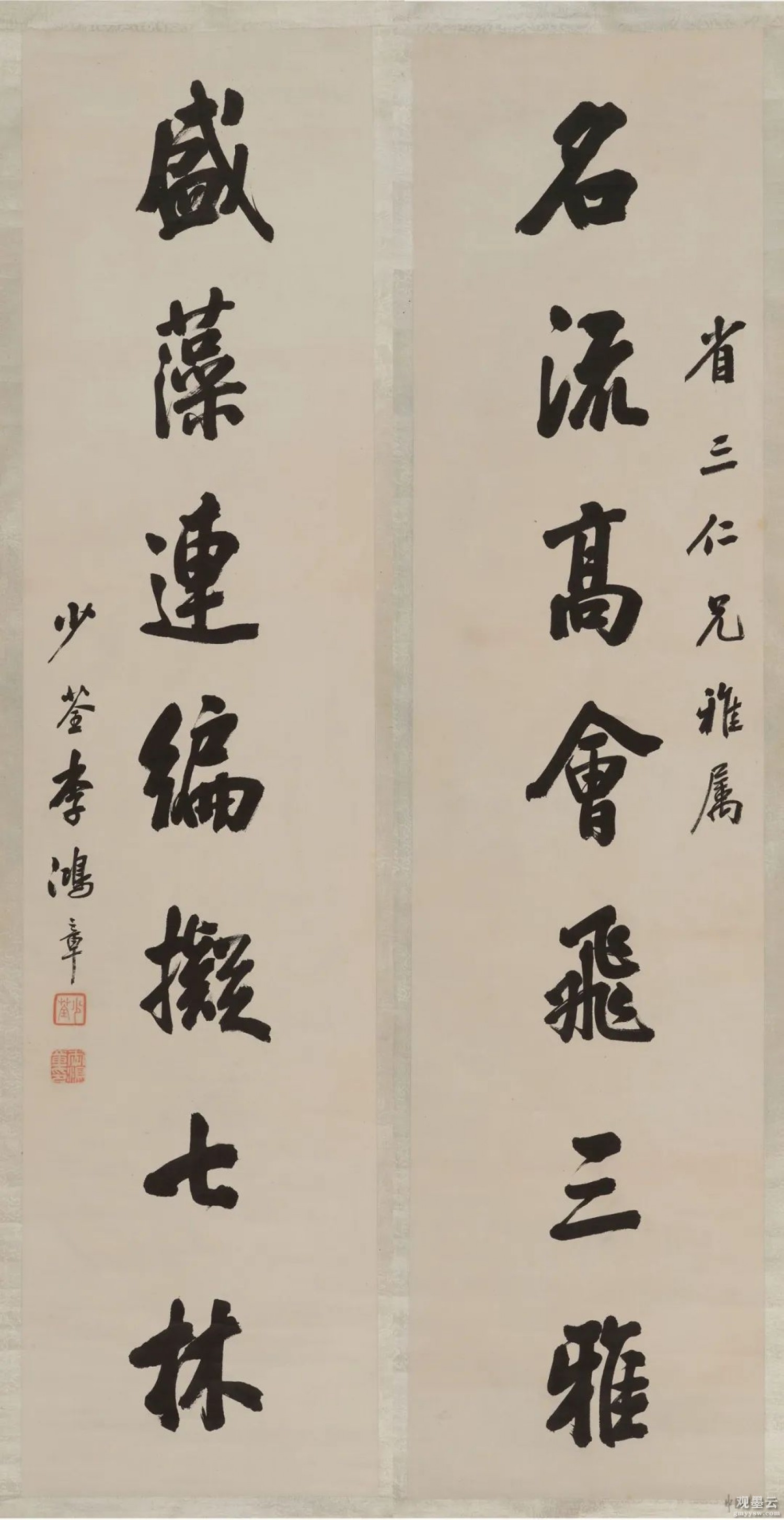
李鸿章(1823年—1901年),字子黻,号少荃,安徽合肥市人。道光二十七年中进士(24岁),授武英殿纂修,嗣后仕途畅通,先后任江苏巡抚,太子太保、两江总督、湖广总督、直隶总督、两广总督、北洋大臣等职务。1901年在北京去世,谥文忠,晋封一等侯。著有《李文忠公全集》、《李肃毅伯奏议》及大量书札信函等。
李鸿章是一位对中国近代史有重要影响的人物。其通过科举步入政坛,文武兼备,在清末叱咤风云几十年。人们在评述其功过是非中,逐步注意到他的书法艺术。通过其存世的大量墨迹,可看到他在书法上的功底,称其为书法家并不为过。